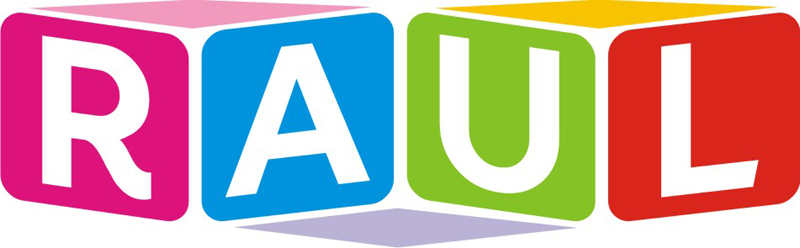
Font name: | Square Kids |
Author: | Grafito Design |
Note by Grafito Design | |
Es una fuente creada para dar la ilusión de que es un dado didactico, creado para un logo de una guarderia It is a font created to give the illusion that it is a dice didactic, a logo created for a nursery |